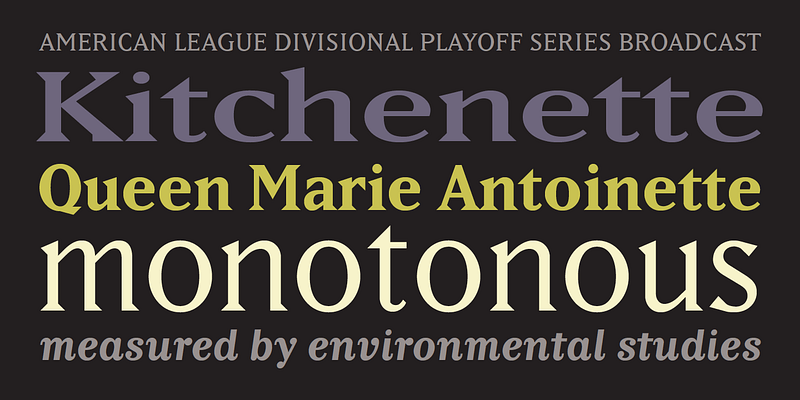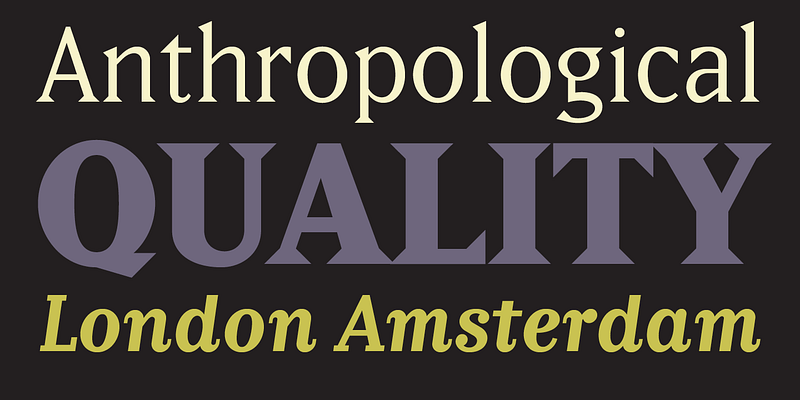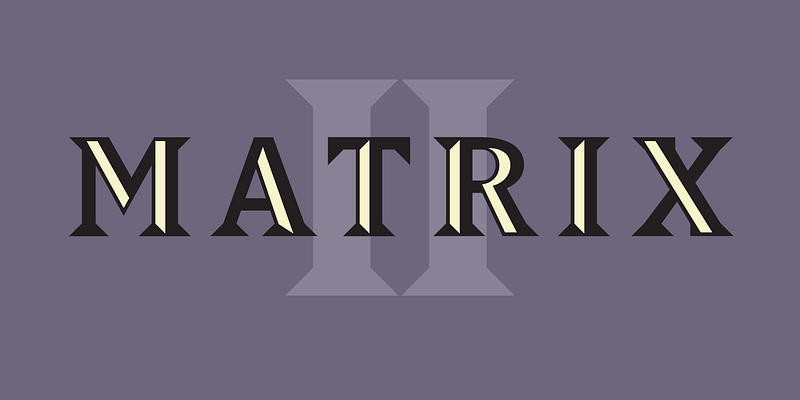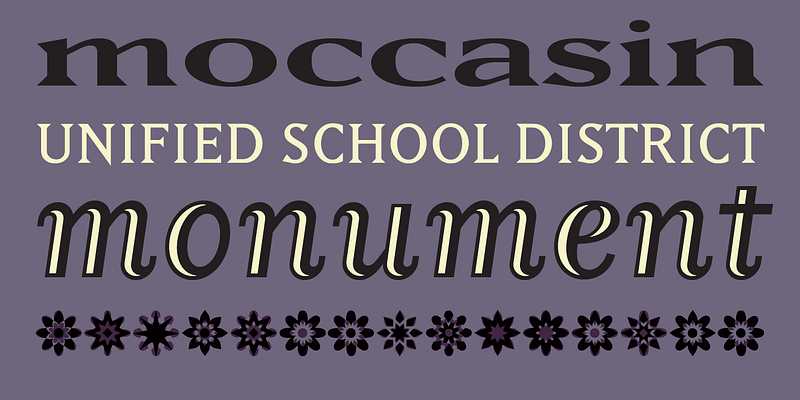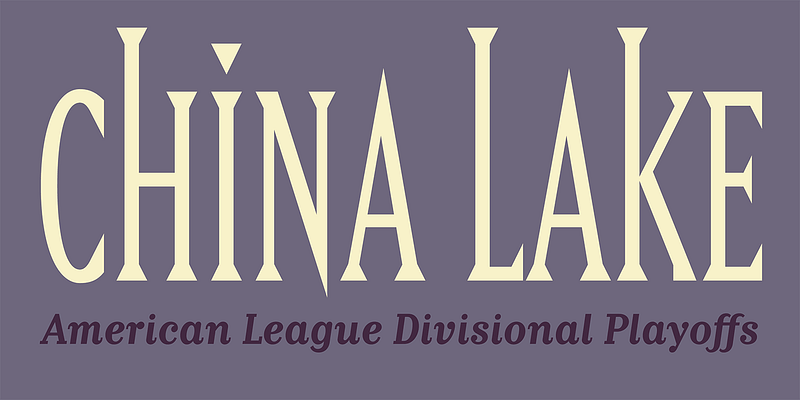
Matrix II는 1986년 주자나 리코(Zuzana Licko)가 디자인한 Matrix 타이프 패밀리를 완전히 재작업한 것입니다.
2007년 1월에 시작된 이 재작업은 Matrix의 OpenType 버전을 만들어야 할 필요성에 의해 시작되었습니다. 말하자면 후드가 열린 상태에서 Licko는 약 20년 전에 디자인된 기존 문자의 많은 부분을 미세 조정하고 정교하게 조율한 것입니다. 경우에 따라 굵은 획과 가는 획의 대비가 감소하고 오버슈트가 수정되었습니다. 다양한 문자의 너비가 조정되고 균일화시켰습니다. f의 교차 획은 대부분의 두께에서 단순화되었습니다. 소문자 g의 디자인을 재검토하고 대체 단층 버전을 디자인하여 OpenType 버전에 추가했습니다.
Semi Narrow, Semi Wide, Semi Tall, Inline Italic 및 Matrix Script의 덜 화려한 버전인 Italic의 3가지 두께로 구성된 패밀리에 7개의 새로운 글꼴이 추가되었습니다. 이 버전을 원본 Matrix와 명확하게 구분하고 이전 버전과의 충돌을 피하기 위해 이름을 Matrix II로 변경했습니다.